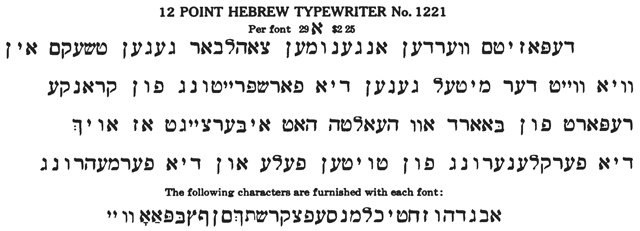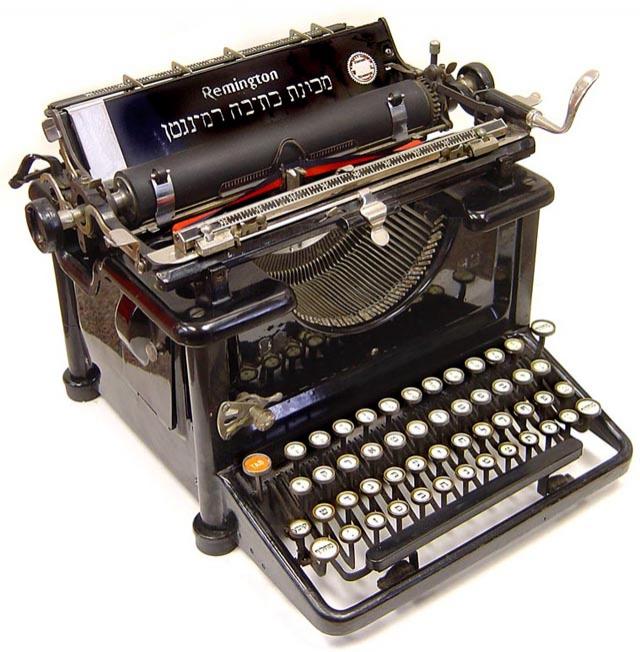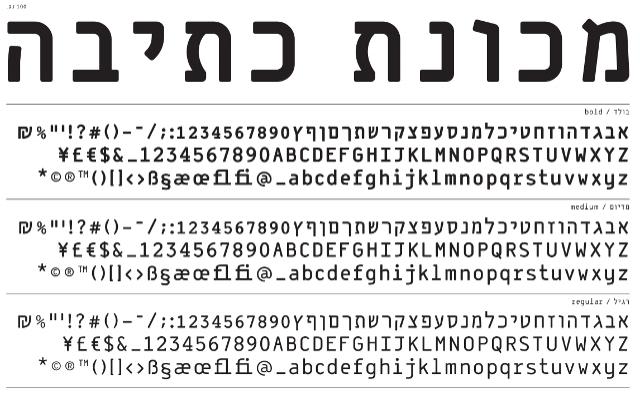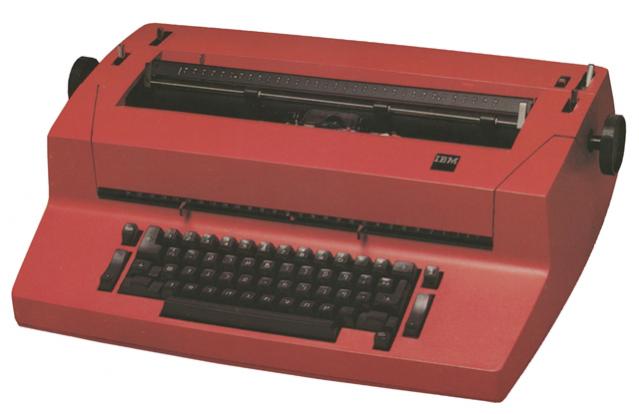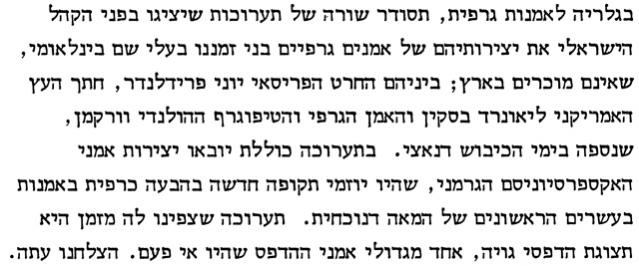
מכונת כתיבה – Hebräisch auf der Schreibmaschine
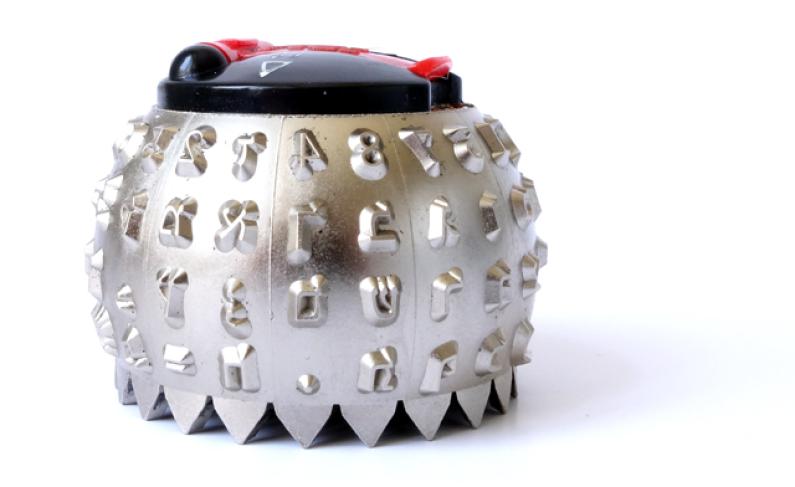
Die Anfänge der hebräischen Schreibmaschine fallen zusammen mit dem Aufkommen des Zionismus, der nationaljüdischen Idee, Ende des 19. Jh. So meldete im Februar 1898 Die Welt, das von Theodor Herzl gegründete deutschsprachige Zentralorgan der zionistischen Bewegung, dass jüngst von der Yost Typewriter Company eine Schreibmaschine mit hebräischen Lettern fertiggestellt worden sei. [1] Das Verdienst ihrer Konstruktion gebühre dabei Moses Gaster, dem sephardischen Oberrabiner Englands, der 1897 auch als Vizepräsident des Ersten Zionistenkongresses geamtet hatte. Dieser habe sich zuerst eine solche Maschine für den eigenen Gebrauch zusammengestellt. [2] Ob es sich bei Gasters hebräischer Schreibmaschine tatsächlich um die erste ihrer Art handelt ist nicht endgültig geklärt. Eine weitere Anwärterin ist eine Blickensderfer Nr. 5 mit hebräischen Typen, die sich in der historischen Sammlung des Technikmuseums MadaTech in Haifa befindet und die Eliezer Ben-Yehuda, dem Autoren des ersten modernen hebräischen Wörterbuchs, zugeschrieben wird. [3] Bei der 1893 erstmals vorgestellten Blickensderfer handelte es sich um eine leichte Reiseschreibmaschine mit zylindrischem Typenrad. Die Typenradtechnologie erlaubte einen vergleichsweise einfachen Austausch der Schriften. [4] Allerdings konnte sich der von Blickensderfer favorisierte radförmige Typenträger für Schreibmaschinen nicht durchsetzen. Das Rennen machten (vorerst) Maschinen mit Typenhebeltechnik, wie sie zu dieser Zeit in den USA vor allem Underwood und Remington produzierten. Im Zug der Verbreitung des mechanischen Schreibens in den ersten Jahrzehnten des 20. Jh. brachten viele der grossen Marken auch Schreibmaschinen mit hebräischen Typen und entgegengesetzter Wagenbewegung auf den Markt.
Hebräische Version der Typenhebelschreibmaschine Remington 92 (1929) [5]
Im Gegensatz zum lateinischen Schriftsystem bildeten sich allerdings keine spezifischen hebräischen Schreibmaschinenschriften heraus. Solche müssen grundsätzlich sehr robust sein, ihre Lesbarkeit muss auch im Fall von mehreren Durchschlägen gewährleistet bleiben. Daher verbieten sich zu feine und dünne Striche. Um das Zuschmieren der Punzen zu verhindern dürfen diese aber auch nicht sehr dick sein. Typische Schreibmaschinenschriften haben eine einheitliche Strichstärke und betonte Serifen. Letztere dienen dabei nicht zuletzt der optischen Anpassung besonders schmaler Zeichen an den strikt proportionalen Schreibmaschinensatz. [6] Obwohl mit der Druckschrift Miriam seit Mitte der 1920er Jahre eine monolineare Hebräisch zur Verfügung stand, die den Ansprüchen an eine Schreibmaschinenschrift bereits weitgehend entsprach, [7] kamen bei hebräischen Schreibmaschinen meist mehr oder weniger zweifelhafte Adaptionen der Meruba, der klassischen hebräischen Druckschrift, zum Einsatz.
Von der Schriftgiesserei American Type Founders (ATF) angebotene hebräische resp. jiddische Schreibmaschinenschrift (1912) [8]
Ernsthafte Bemühungen, die hebräischen Schreibmaschinenschriften besser zu machen, d.h. vor allem lesbarer zu gestalten, sind vereinzelt erst in der zweiten Hälfte des 20. Jh. zu beobachten. So gelangte beispielsweise die Schweizer Firma Paillard & Cie., die mit ihrer Marke Hermes auch im hebräischen Markt eine wichtige Rolle spielte, an den israelischen Typographen und Schriftgestalter Henri Friedlaender mit der Anfrage, für sie eine schreibmaschinentaugliche Version seiner Druckschrift Hadassah zu zeichnen.
Für die Hermes-Schreibmaschine umgearbeitete Fassung der Hadassah von Henri Friedlaender (1964) [9]
Bei Typenhebelmaschinen bedeutete der Austausch des Schriftsystem allerdings zwingend immer auch den Austausch der Maschinen. Der leichte Wechsel zwischen verschiedenen Schriften und Schriftsystemen war mit dieser Technik nicht möglich. Eine Änderung brachte erst die Abkehr von der Typenhelbeltechnik durch das von IBM in den 1960er Jahren mit der Selectric eingeführte Kugelkopf-System, bei dem die zu schreibenden Zeichen auf einem auswechselbaren Element angeordnet sind das aufgrund seiner Form und Grösse auch «Golfball» genannt wurde [Bild am Artikelanfang].
Ein Meilenstein für hebräisch bzw. mehrsprachig Schreibende war die Einführung der Selectric II 1971. Eine der Neuerungen dieser Maschine gegenüber ihrer Vorläuferin, war die Möglichkeit, mittels einer Taste die Schreibrichtung umzustellen. Da der Kugelkopf 88 belegbare Positionen bot, erlaubte das System nicht nur zwei verschiedene Schriftgrössen auf einem Schreibkopf unterzubringen, sondern auch unterschiedliche Alphabete. Es war mit dieser Maschine damit möglich ohne Wechsel des Typenträgers zwischen lateinischer und hebräischer Schrift zu wechseln. Mitte der 1970er-Jahre begann IBM in Israel eine hebräisch/lateinisch bestückte Selectric II unter dem Namen Kadurit («Ball/Kugel») zu vermarkten. [10]
Logo von IBM Israel und ein Modell der Kadurit mit Löschfunktion (um 1980) [11]
Ebenfalls auf dem Kugelkopfsystem aufbauend war der IBM-Composer. Als eigenständige Drucktechnologie neben Blei- und Photosatz bot der Composer eine Vielzahl von Layout-Möglichkeiten und erlaubte – im Gegensatz zu dem für die Schreibmaschine typischen festen Zeichenabstand – eine proportionale Buchstabenlaufweite. [12] Für Kadurit und Composer entwarf Henri Friedlaender, drei Schriften: Shalom, Hadar und Aviv, die alle als Pendant zu lateinischen Schriften konzipiert waren. [13] Besondere Aufmerksamkeit verdient dabei die als hebräisches Pendant zur serifenlosen Gothic von Robert Robertson entworfene Aviv.
Mit Aviv schuf der damals bereits siebzigjährige Typograph eine serifenlose Schrift mit visuell gleichen Strichdicken und einer sehr eigenen, dezidiert technischen und gleichzeitig weichen Anmutung. Die Weichheit des Entwurfs mit seinen abgerundeten Ecken entspricht nicht zuletzt auch dem generellen Charakter von Schreibmaschinenschriften, da ein scharf konturiertes Schriftbild mit Farbband-Durchschlag kaum möglich ist.
Gewürdigt wurde Friedlaenders Schrift durch eine digitale Neuinterpretation der Schriftgestalter/innen des Kollektivs Hagilda [15]. Ergänzt um ein lateinisches Pendant publizierten diese 2007 unter dem Namen Arbel Hagilda eine Schrift im Geiste der Selectric. Bei ihrem Entwurf waren die Gestalter*innen allerdings nicht mehr an die technischen Voraussetzungen der Schreibmaschine gebunden. Arbel Hagilda entspringt gänzlich der digitalen Welt. Ihre Formen fungieren als Verweis auf eine vergangene Epoche.
Aber auch unter digitalen Bedingungen ist Schriftgestaltung nicht voraussetzungslos. Das macht Hagilda in ihrer Selbstdarstellung deutlich wenn das Kollektiv den Ursprung des Unternehmens 2002 in Verbindung bringt, mit der durch das Ende der 1990er-Jahre etablierten OpenType-Format gegebenen Möglichkeit, hebräische wie auch lateinische Ausprägungen eines Schriftentwurfs in einer einzigen Schriftartdatei (Font) unterzubringen.